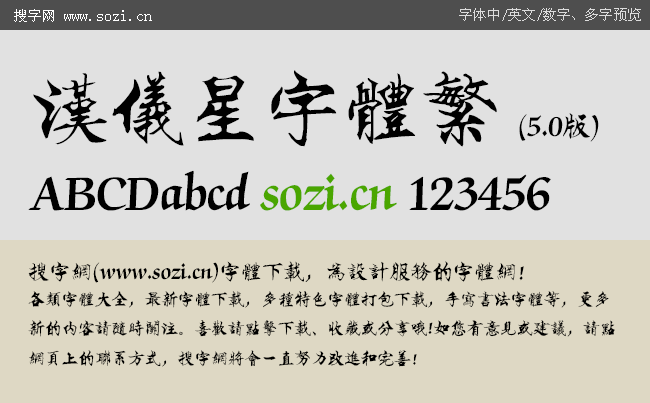
漢儀星宇體繁
搜字網(wǎng)提供一款漢儀星宇體繁中文字體下載,漢儀星宇體是一款蒼勁有力的藝術(shù)字體,該字體筆鋒犀利,粗細(xì)大小不一,字體端莊大方,筆畫之間十分有力量,適用于廣告設(shè)計、平面設(shè)計、印刷包裝、藝術(shù)設(shè)計、網(wǎng)站設(shè)計領(lǐng)域。